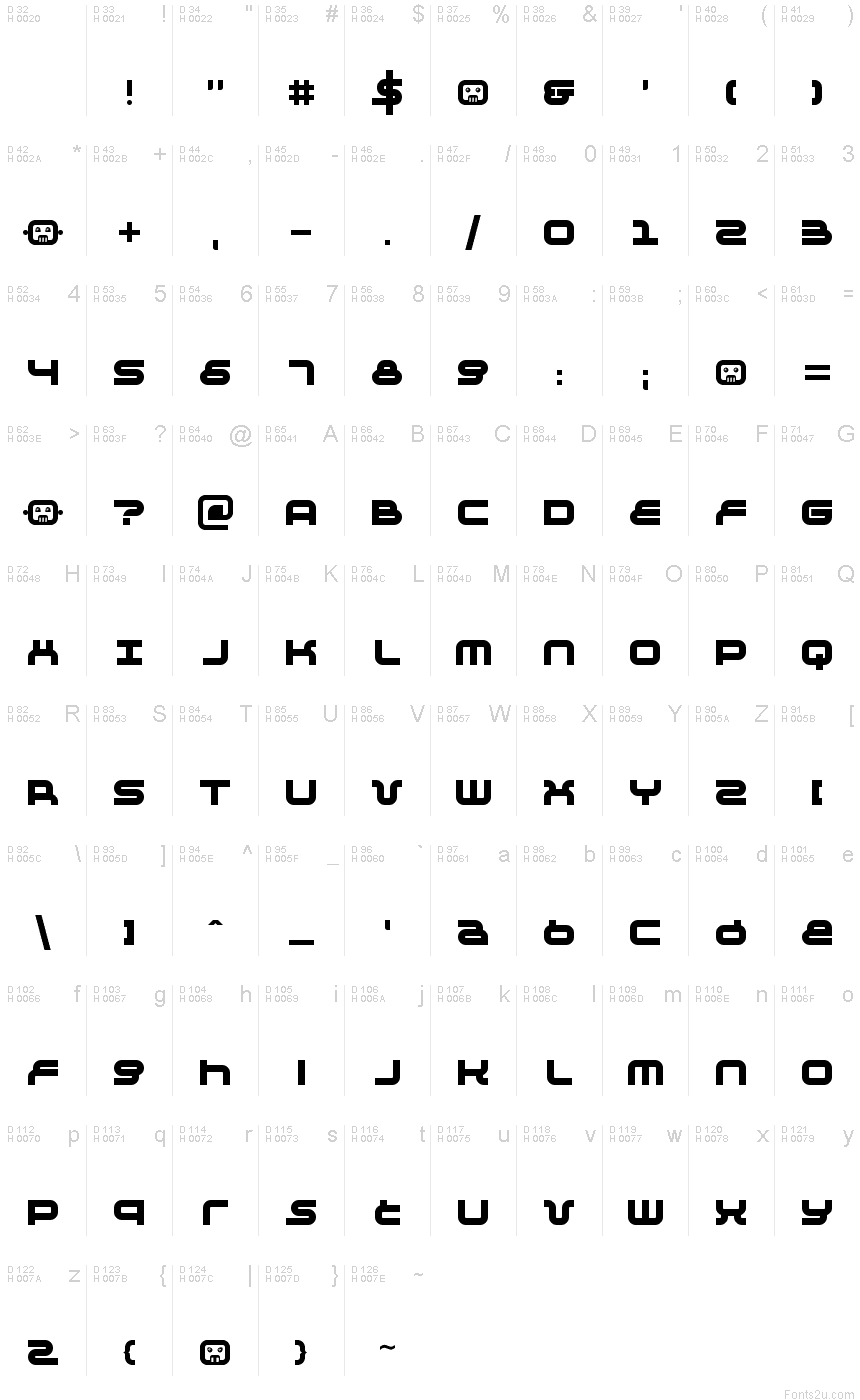
Negative 24 di duysBUST Fonts è un carattere display futuristico gratuito, caratterizzato da forme arrotondate e squadrate e da profondi tagli interni che conferiscono a ogni glifo una struttura fresata in stile arcade. Le curve ripetute e le spalle piatte mantengono un aspetto meccanico, mentre i centri aperti aggiungono un preciso ritmo stencil integrato.
Negative 24 è un font gratuito che funziona alla grande per poster sci-fi, loghi di videogiochi, flyer di eventi, schermate di avvio di app e branding tecnologico, quando desideri un titolo distintivo. Le sue aperture sagomate e le forme compatte si adattano perfettamente anche a titoli, dettagli per poster, copertine di album e design di etichette che richiedono un tocco industriale, netto e codificato.